無料&商用利用可能!おすすめのおしゃれで美しい英語セリフフォント
本記事では、無料&商用利用可能なセリフフォントを紹介します。
スクリプトフォントやサンセリフフォントに比べると、あまり多くない印象の無料セリフフォントですが、がんばって探してきました。
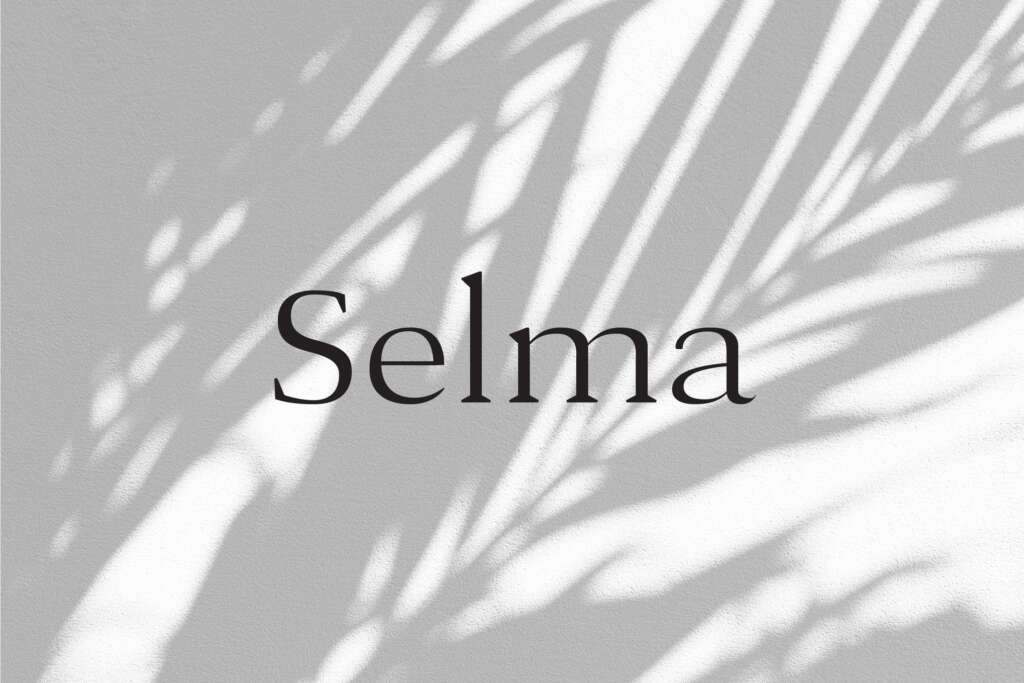
▼太め&細めラインのコントラストが特徴のセリフフォント「Cavas Nera – Free Elegant Serif Font」。商用利用可能です。ダウンロード方法はこちら
▼流れるようなスウォッシュが特徴的でエレガントなセリフフォント「ROKUROU DISPLAY FONT」。商用利用可能です。ダウンロード方法はこちら
▼Pixel Surplusで無料配付中の今っぽいセリフフォント「NEW YORK – FREE FONT」。Desktop Commercial Use Licenseです。ダウンロード方法はこちら
▼Pixelbuddhaから、セリフ&スクリプトフォントのセット「North Avellion Font Duo」。商用利用可能です。ダウンロード方法はこちら
▼Pixel Surplusの「HAIGRAST – FREE FONT DUO」は、セリフフォントとスクリプトフォントを収録。ダウンロード方法はこちら
▼Pixel Buddhaのクラシックな印象のセリフフォント「Lansdowne Decorative Font」。ダウンロード方法はこちら
▼Pixel Buddhaのデザイン性の高い無料セリフフォント「Moalang Display Font」。ブランディングやラベルデザインなどで映える書体です。ダウンロード方法はこちら
▼Pixel Buddhaの商用利用可能な無料セリフフォント「Botera Stencil Font」。ステンシル風のユニークな書体です。ダウンロード方法はこちら
▼Pixel Buddhaの商用利用可能な無料セリフフォント「The Circus Display Font」。レトロ風なロゴ作りにもオススメ。ダウンロード方法はこちら
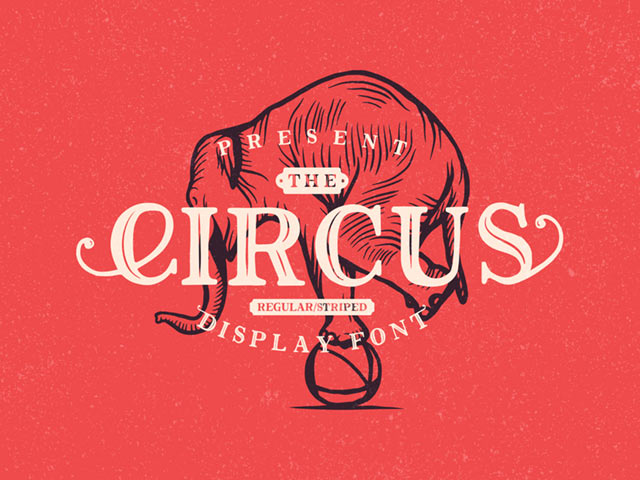
▼Pixel Buddhaの商用利用可能な無料セリフフォント「Modernist Milk Stencil Font」は、ギリギリ読める範囲だけ残したウロコが印象的。ダウンロード方法はこちら
▼Pixel Buddhaの商用利用可能な無料セリフフォント「Realist Typeface」は文字ごとに大小のメリハリをつけて使うといい感じ。ダウンロード方法はこちら
▼Pixel Buddhaの商用利用可能な「Unchained Font Family」は西部劇っぽいスラブセリフ書体。ダウンロード方法はこちら
▼Pixel Surplusのレトロなセリフフォント「RESTORA」は合字(リガチャ)もしっかりデザイン済み。ダウンロード方法はこちら
▼Pixel Surplusの商用利用可能な無料セリフフォント「SHAMERY」は使いやすいベーシックさが魅力。ダウンロード方法はこちら
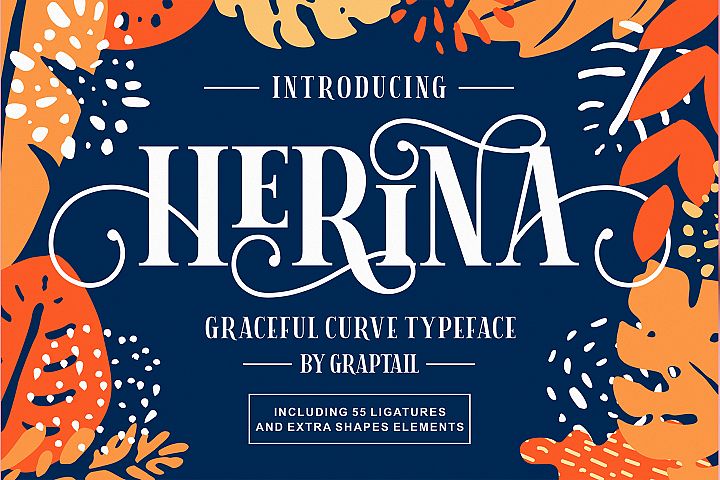
▼Pixel Surplusのクリスマステイストの無料セリフフォント「CHRISTMAS」。ダウンロード方法はこちら
▼Pixel Surplusから、丸いウロコが特徴の無料セリフフォント「ZOIKA」。ダウンロード方法はこちら
▼Pixel Surplusから、ボディのメリハリが効いたフリーフォント「FOERTE」。ダウンロード方法はこちら
▼Pixel Surplusから、ところどころいびつにカットされたような書体「RUDE」。ダウンロード方法はこちら
▼Pixel Surplusから、細長いデザイン書体「EN GARDE」。ダウンロード方法はこちら
▼Pixel Surplusから、スラブセリフ書体の「WANDERLUST」。ダウンロード方法はこちら
▼Pixel Surplusから、レギュラー・ラフ・ラウンドの3パターンの書体を収録した「UNDERSTOCK」。ダウンロード方法はこちら
▼Pixel Surplusから、85言語に対応したセリフフォント「LABOR UNION」。ダウンロード方法はこちら
▼Pixel Surplusから、エレガントなセリフ書体「BEAU」。ダウンロード方法はこちら
▼Pixel Surplusから、スポーツ系のロゴに重宝しそうな「STONEBURG」。ダウンロード方法はこちら
▼Pixel Surplusから、ステンシルのようなセリフフォント「SAINT GEORGE」。ダウンロード方法はこちら
▼Pixel Surplusから、極太ウェイトでラフな印象の「MAVERYK」。ダウンロード方法はこちら
▼Pixel Surplusから、クラシックなデザインセリフ書体「WT BRADFORD」。ダウンロード方法はこちら
▼Pixel Surplusから、クール系のセリフフォント「GEIZER」。ダウンロード方法はこちら
▼Pixel Surplusから、かわいい手書き風セリフフォント「EVA」。ダウンロード方法はこちら
▼Pixel Surplusから、ヴィンテージフォント「HIGH LIFE」。無料版はセリフフォントのみ収録しています。ダウンロード方法はこちら
▼Pixel Surplusから、ヴィンテージ風の7書体を収録した「BERG」。ダウンロード方法はこちら
▼Pixel Surplusから、デザイン性の高いウロコが特徴的な「TRAVELER」。キャンバス地のテクスチャもついてきます。ダウンロード方法はこちら
▼Pixel Surplusから、なんとも素朴な雰囲気を醸し出すフォント「PHALANX」。ダウンロード方法はこちら
▼Pixel Surplusから、かわいいヴィンテージの手書き風フォント「BARTOLOMEW」。ダウンロード方法はこちら
▼Pixel Surplusから、プレスされたような掠れたテクスチャが魅力の「BLACK MASK」。ダウンロード方法はこちら
▼Dealjumbo.comから、カールしたエッジ部分が特徴的な「Nugie Romantic」。
▼Dealjumbo.comから、シャープな雰囲気がかっこいい「Asmath Serif」。